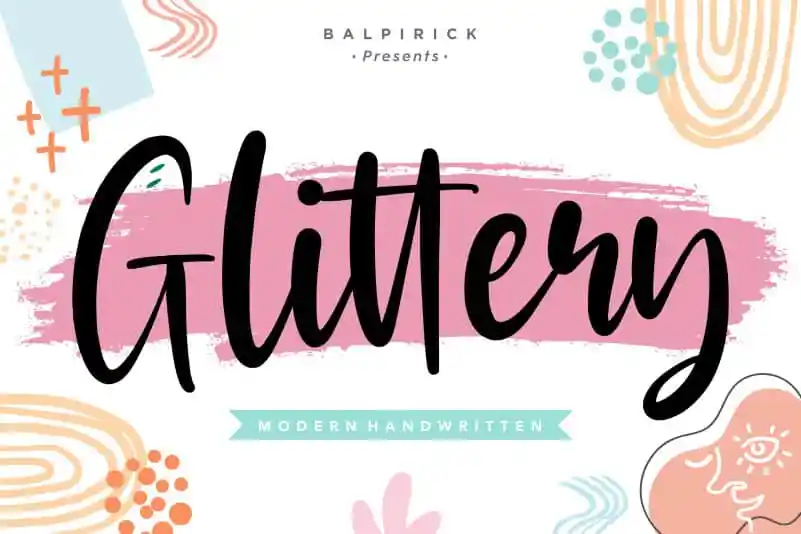
Glittery Modern Handwritten Font – Fonte Grátis
Glittery Modern Handwritten Font
Glittery Modern Handwritten Font é uma fonte criada pelo designer balpirick que combina a elegância moderna com linhas suaves e curvas romanas. Este tipo de letra dá um toque sofisticado e chique às criações, sendo perfeito para aplicação em diversos projetos como embalagens de produtos, identidades corporativas, revistas, redes sociais, convites de casamento ou apenas quando se deseja destacar os textos sobre o fundo. Suas linhas suaves e a personalidade moderna da fonte criam uma imagem contemporânea e encantadora que certamente dará um toque especial a qualquer projeto. Glittery Modern Handwritten Font é perfeita para quem busca estilo, charme e sofisticação em suas criações digitais.